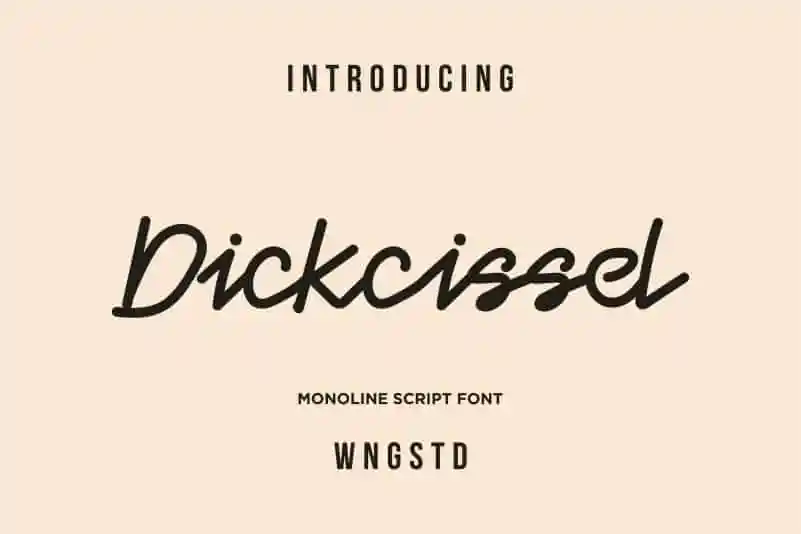
Dickcissel Monoline Font – Download Grátis
A Dickcissel Monoline é uma elegante tipografia escrita a mão, que proporciona uma sensação suave e equilibrada. Esta fonte tem um toque delicado e natural que se sobressai perfeitamente, garantindo uma fluidez única e encantadora ao escrever qualquer texto criativo. A Dickcissel Monoline é ideal para os designers que desejam adicionar um elemento único a seus trabalhos de arte digital ou impressão. Com sua delicadeza característica, esta fonte será o ponto focal perfeito em qualquer projeto, tornando cada letra uma verdadeira obra de arte única. Quebre as barreiras e explore essa poderosa tipografia escrita a mão da WNGSTD.